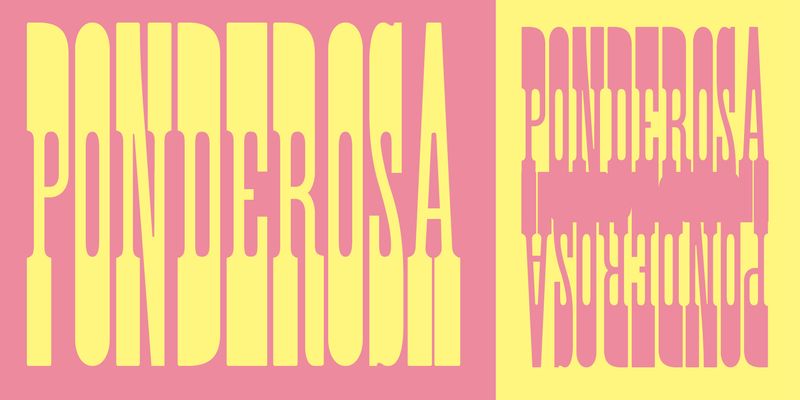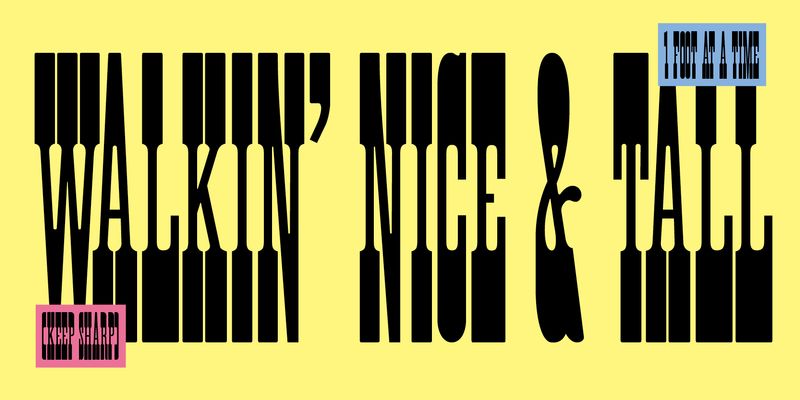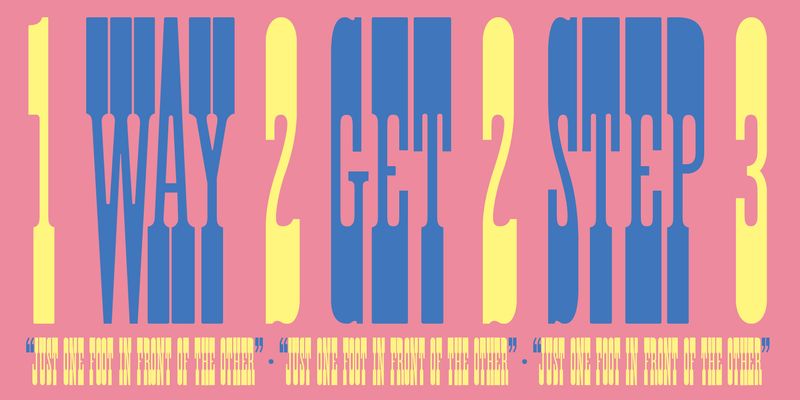
Kim Buker Chansler a conçu Ponderosa, une police Adobe Originals, en 1990 pour la série Adobe Wood Type.
Le programme Adobe Originals a débuté en 1989 en tant que fonderie typographique interne chez Adobe, réunie pour créer des polices originales d’une qualité de conception, d’une fidélité technique et d’une longévité esthétique exemplaires.
Aujourd’hui, la mission de l’équipe Type est de créer des polices sophistiquées, voire expérimentales, qui explorent les possibilités du design et de la technologie. Les polices publiées sous le nom d’Adobe Originals sont le résultat d’années de travail et d’études, et sont considérées comme les normes de l’industrie pour l’ambition et la qualité de leur développement.